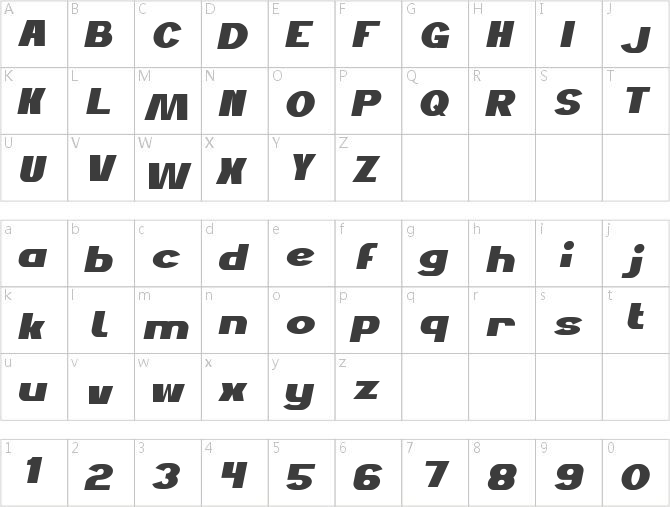
字體名稱: JUST DO
JUST DO GOOD-ITALIC
JUST DO GOOD-ITALIC介紹
JUST DO GOOD-ITALIC字體字庫是一款讓人賞心悅目、百看不厭的英文字體,適合各類廣告和產品包裝設計應用,字體大小0.02MB,格式為ttf字體,上傳用戶是東方時尚,作者/版權方為未知